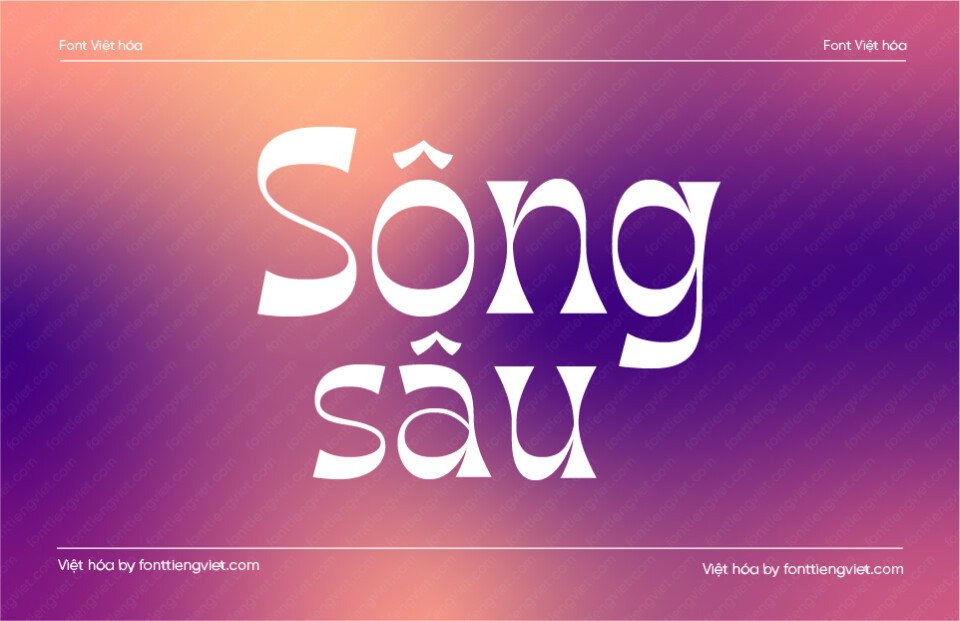
Font Việt hóa 1FTV VIP Morgai Retan
Tải Font Việt hóa 1FTV VIP Morgai Retan Đẹp Mắt Cho Thiết Kế Sáng Tạo
Nếu bạn đang tìm kiếm một bộ chữ mang phong cách cổ điển xen lẫn nét hiện đại, bộ Font Việt hóa 1FTV VIP Morgai Retan chính là sự lựa chọn không thể bỏ qua. Đây là mẫu Font Miễn Phí được tinh chỉnh kỹ lưỡng về dấu tiếng Việt, giúp người dùng dễ dàng ứng dụng vào các dự án thiết kế học đường hoặc trang trí poster. Với những đường nét thanh mảnh nhưng vô cùng sắc sảo, bộ font này tạo nên sự sang trọng và chuyên nghiệp cho mọi văn bản.
Đặc điểm nổi bật của Font Việt hóa 1FTV VIP Morgai Retan
Thiết kế Serif tinh tế và đẳng cấp
Morgai Retan thuộc nhóm font chữ có chân (Serif) với cấu trúc chữ cân đối. Điểm đặc biệt của phiên bản 1FTV VIP chính là khả năng hiển thị mượt mà trên nhiều nền tảng khác nhau từ phần mềm Office đến các công cụ đồ họa chuyên nghiệp. Font Việt hóa 1FTV VIP Morgai Retan mang lại cảm giác hoài cổ, rất phù hợp cho các bài thuyết trình lịch sử hoặc bìa sách nghệ thuật.
Khả năng tương thích cao
Ứng dụng thực tế của font chữ trong giáo dục